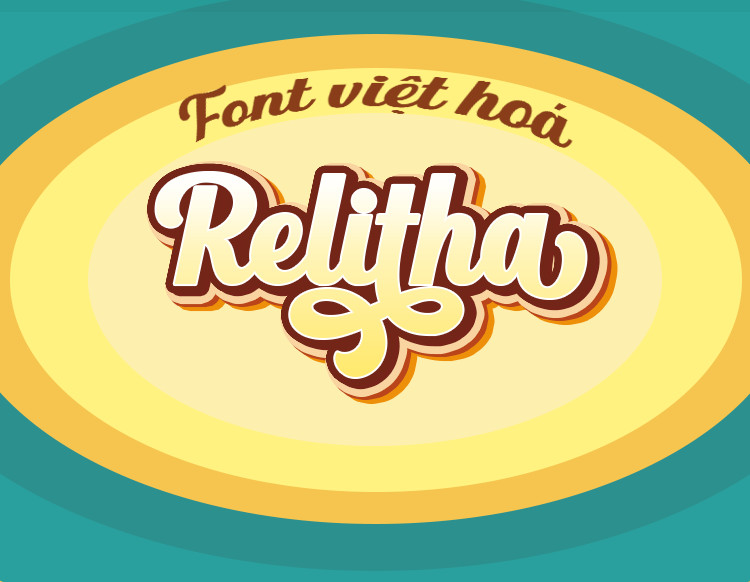
Giới thiệu về bộ Font việt hoá MJ Relitha Script
Trong thế giới thiết kế đồ họa, việc tìm kiếm một mẫu Font Chữ mang đậm nét nghệ thuật nhưng vẫn đảm bảo tính ứng dụng cao là điều vô cùng quan trọng. Font việt hoá MJ Relitha Script chính là sự lựa chọn hoàn hảo cho những ai yêu thích phong cách viết tay mềm mại và uyển chuyển. Đây là một bộ font script hiện đại, được thiết kế với các đường nét tinh tế, tạo cảm giác gần gũi và sang trọng cho mọi bản thiết kế từ thiệp mời, logo đến các ấn phẩm truyền thông trường học.
Ưu điểm nổi bật của Font việt hoá MJ Relitha Script
Nét chữ nghệ thuật và tính linh hoạt
Đặc điểm lớn nhất của bộ font này chính là sự kết hợp giữa phong cách thư pháp truyền thống và xu hướng typography hiện đại. Các ký tự được chăm chút kỹ lưỡng, giúp người dùng dễ dàng tạo ra những tiêu đề bắt mắt. Việc đã được Việt hóa hoàn chỉnh giúp các bạn học sinh và giáo viên sử dụng dễ dàng trong việc soạn thảo giáo án điện tử hoặc làm báo tường mà không lo lỗi font khi gõ dấu tiếng Việt.
Ứng dụng đa dạng trong thực tế
Bên cạnh việc dùng cho các sản phẩm thương mại, bộ font này còn rất phù hợp để trang trí các tài liệu học tập. Với Font việt hoá MJ Relitha Script, bạn có thể biến những đoạn văn bản khô khan trở nên sinh động và có hồn hơn, giúp truyền tải thông điệp một cách cảm xúc nhất đến người xem.